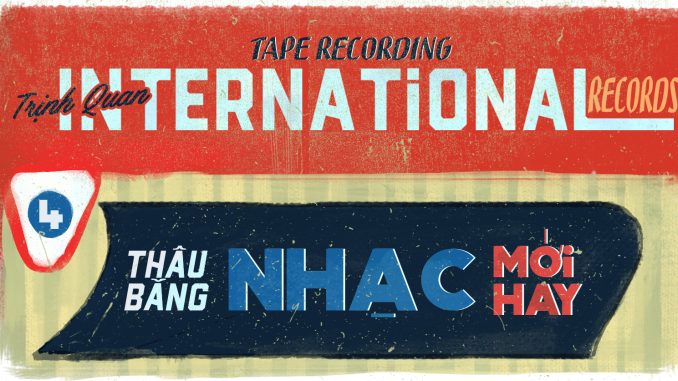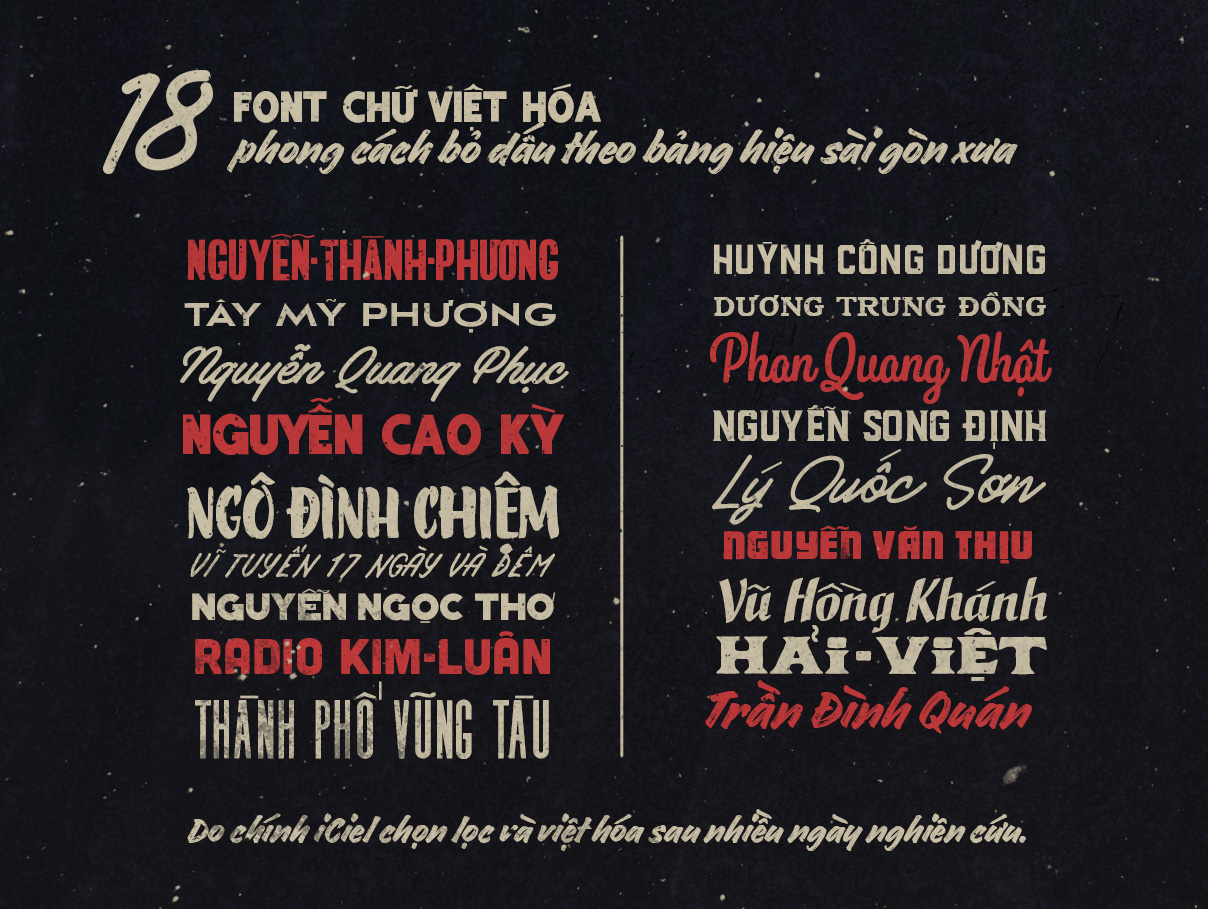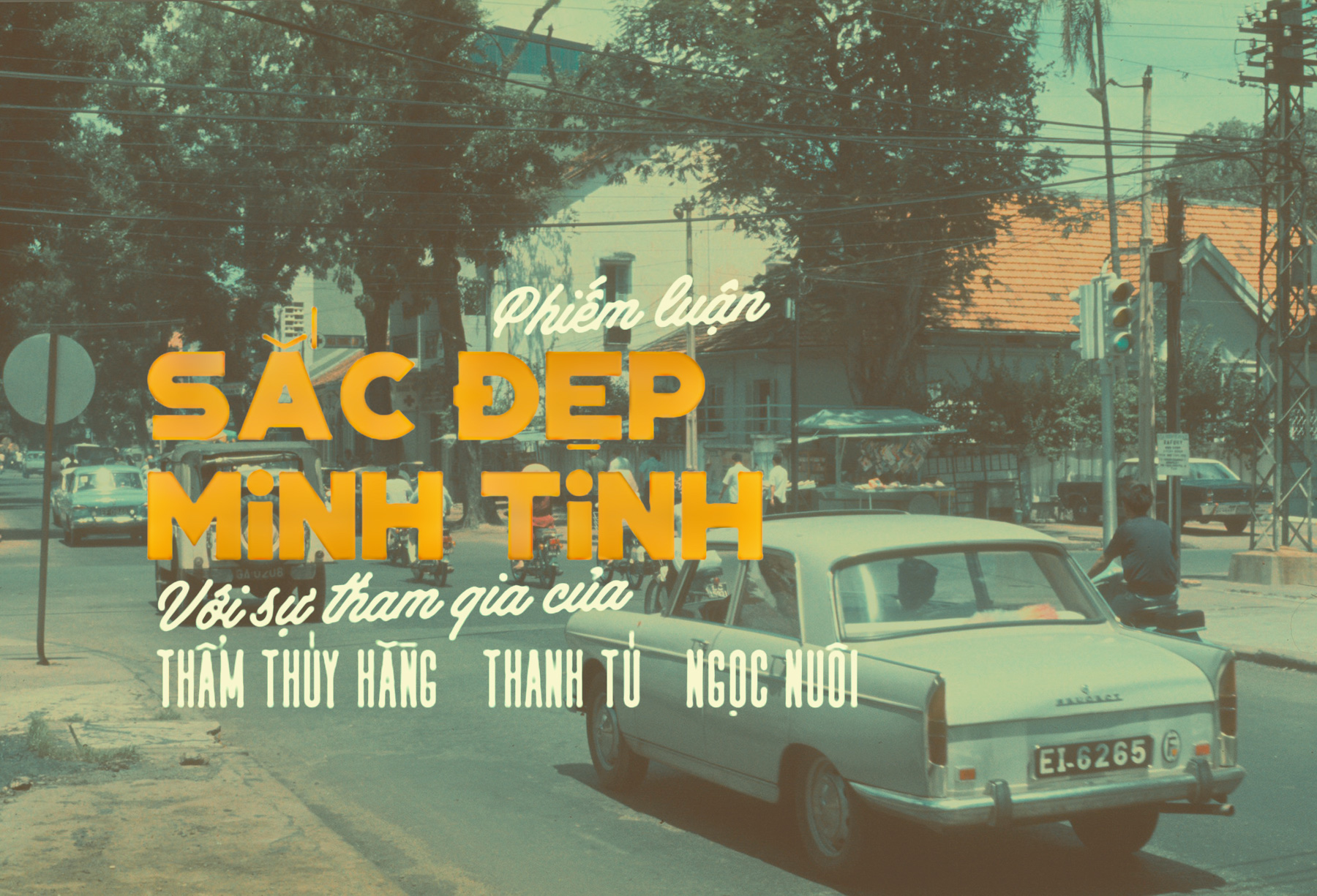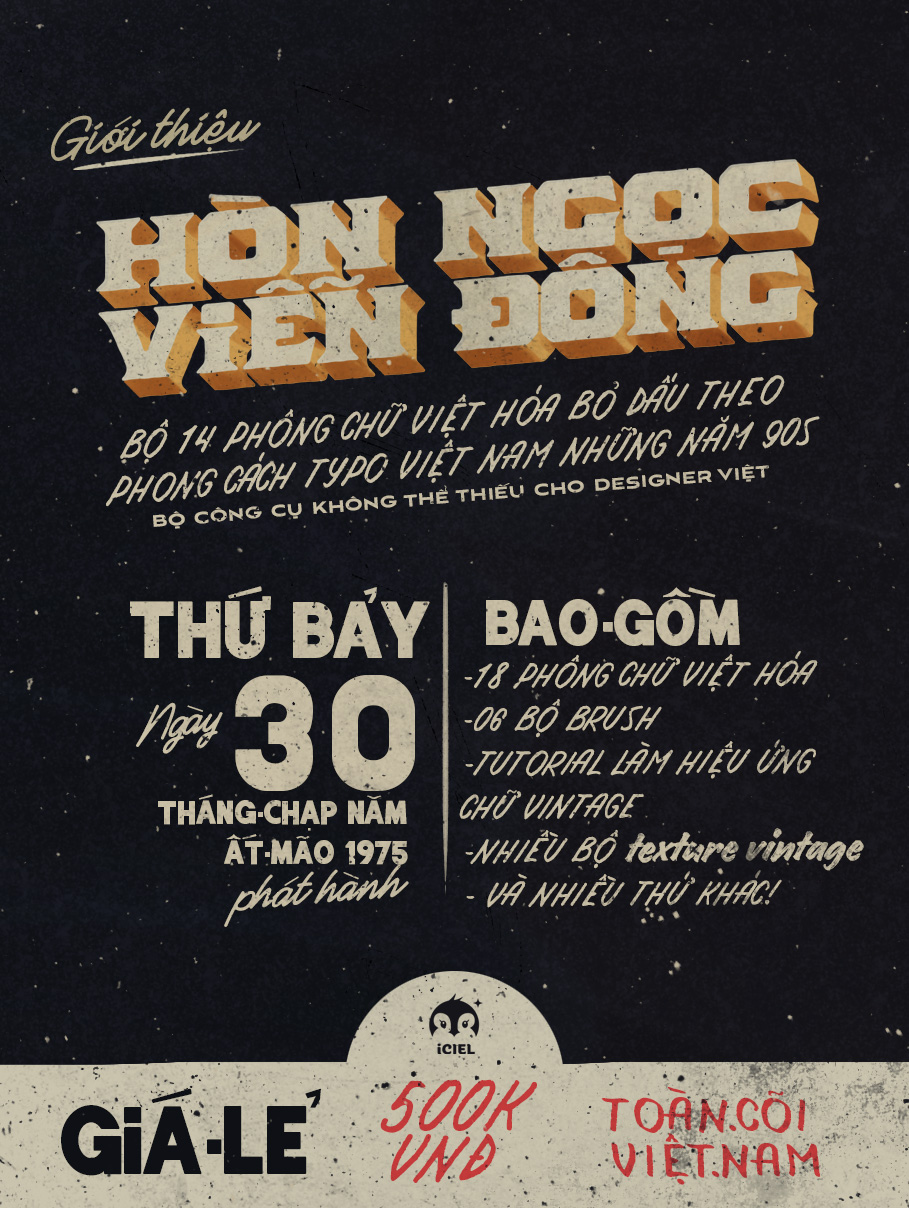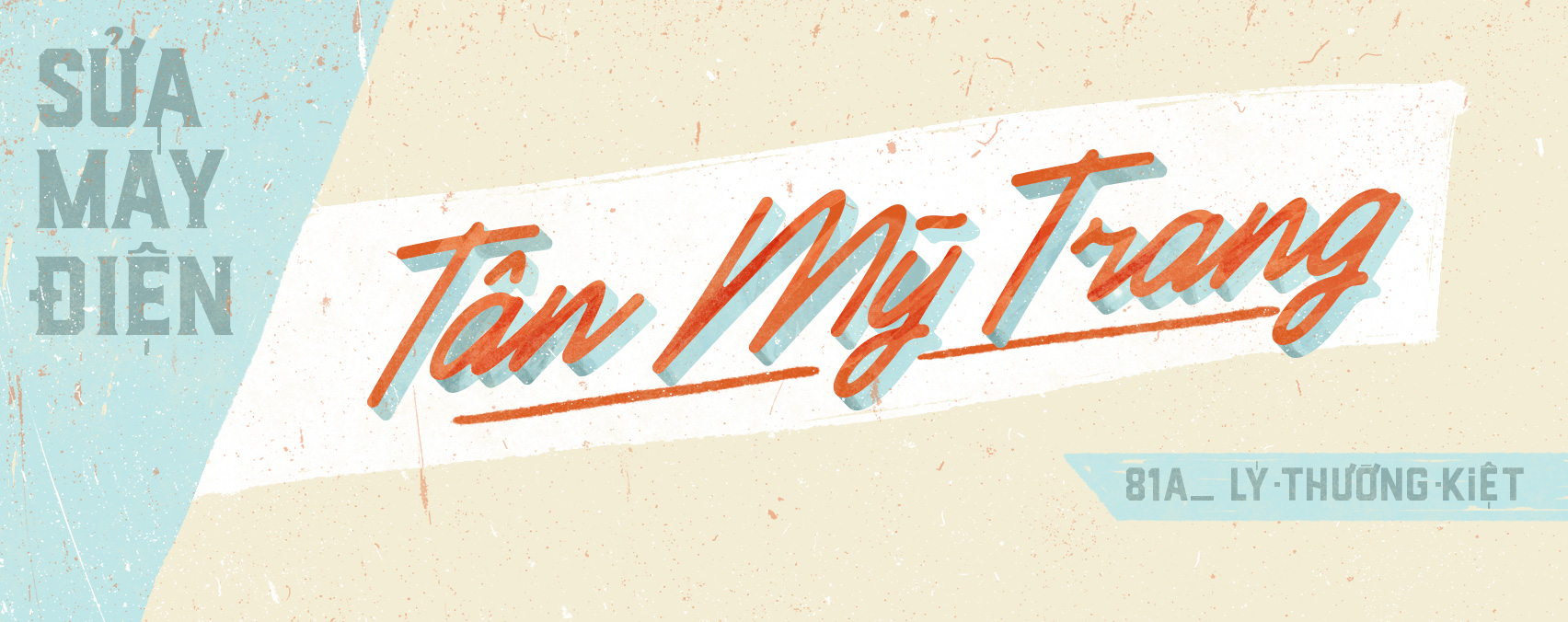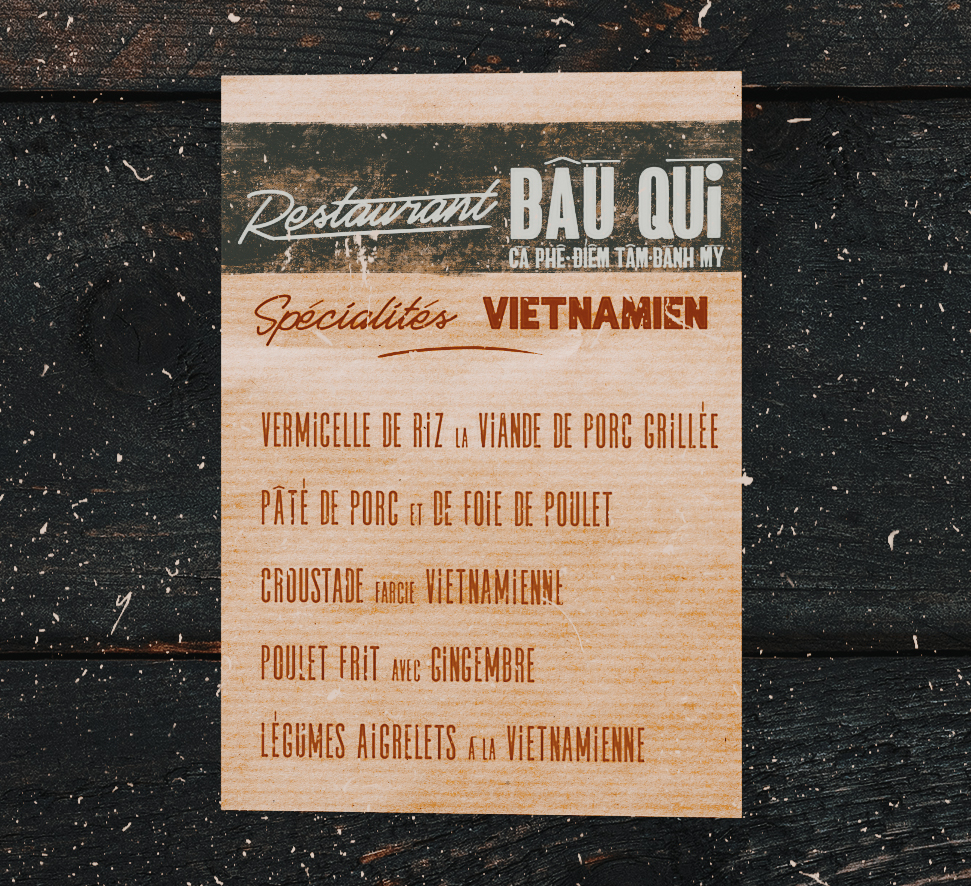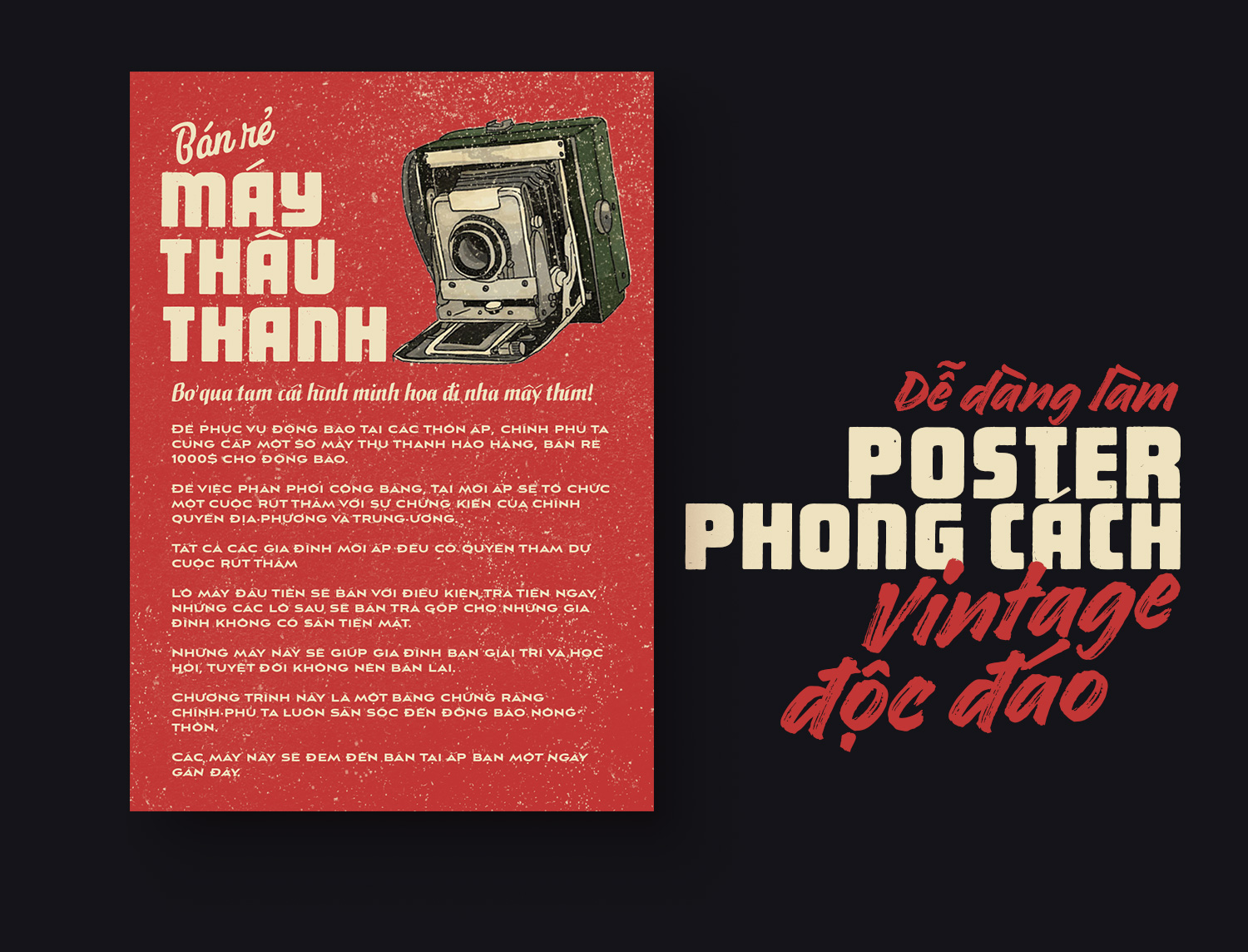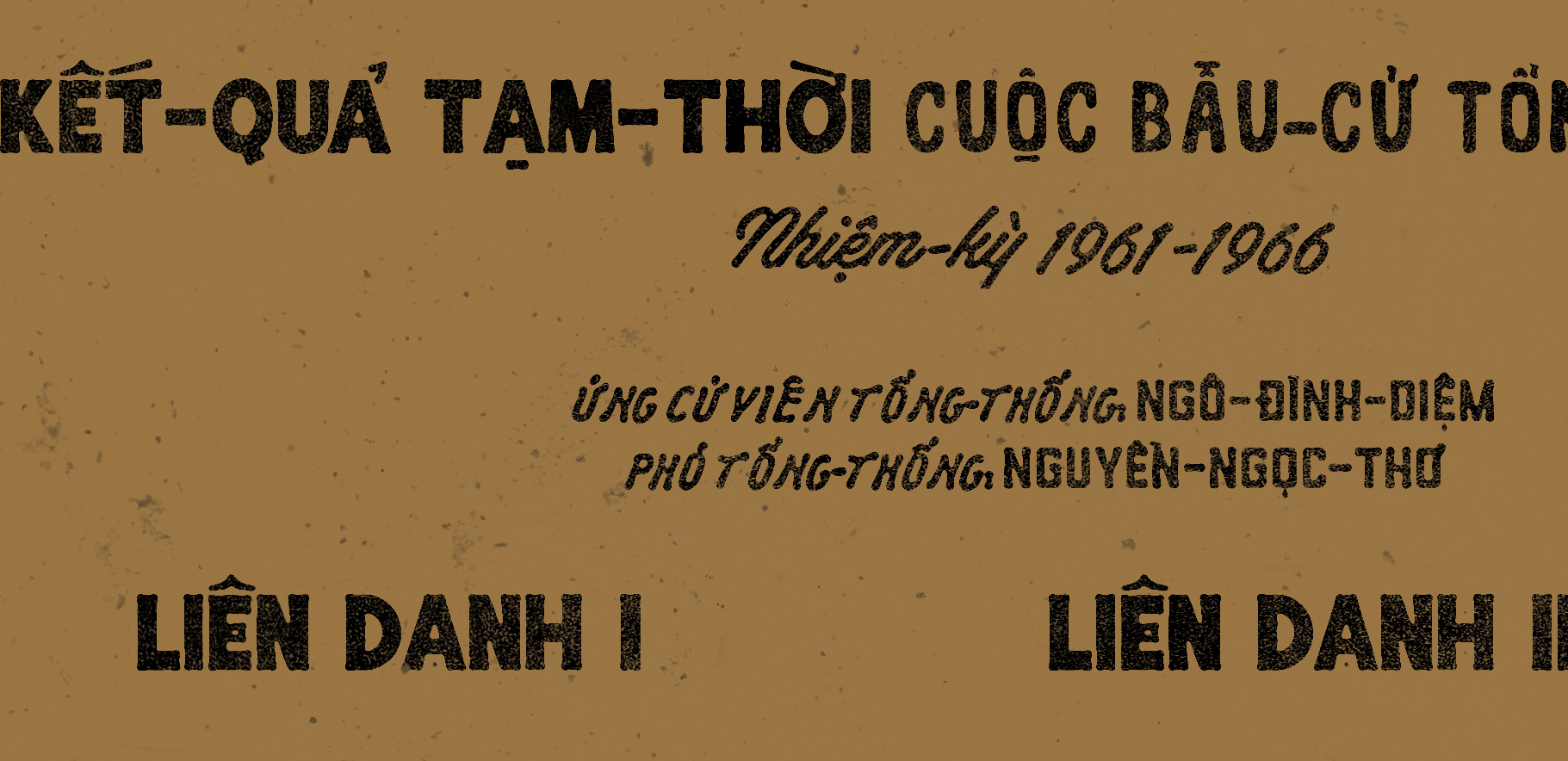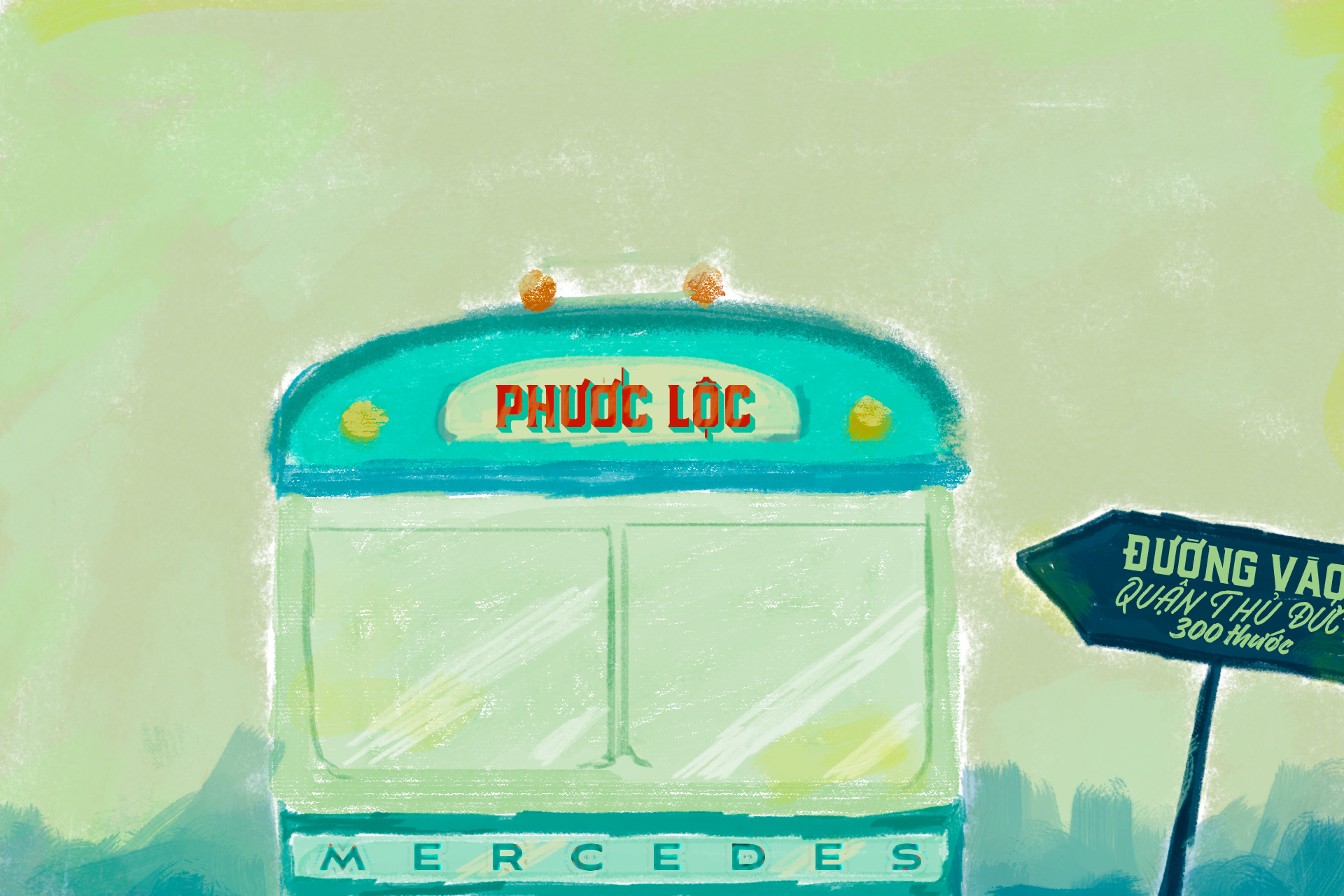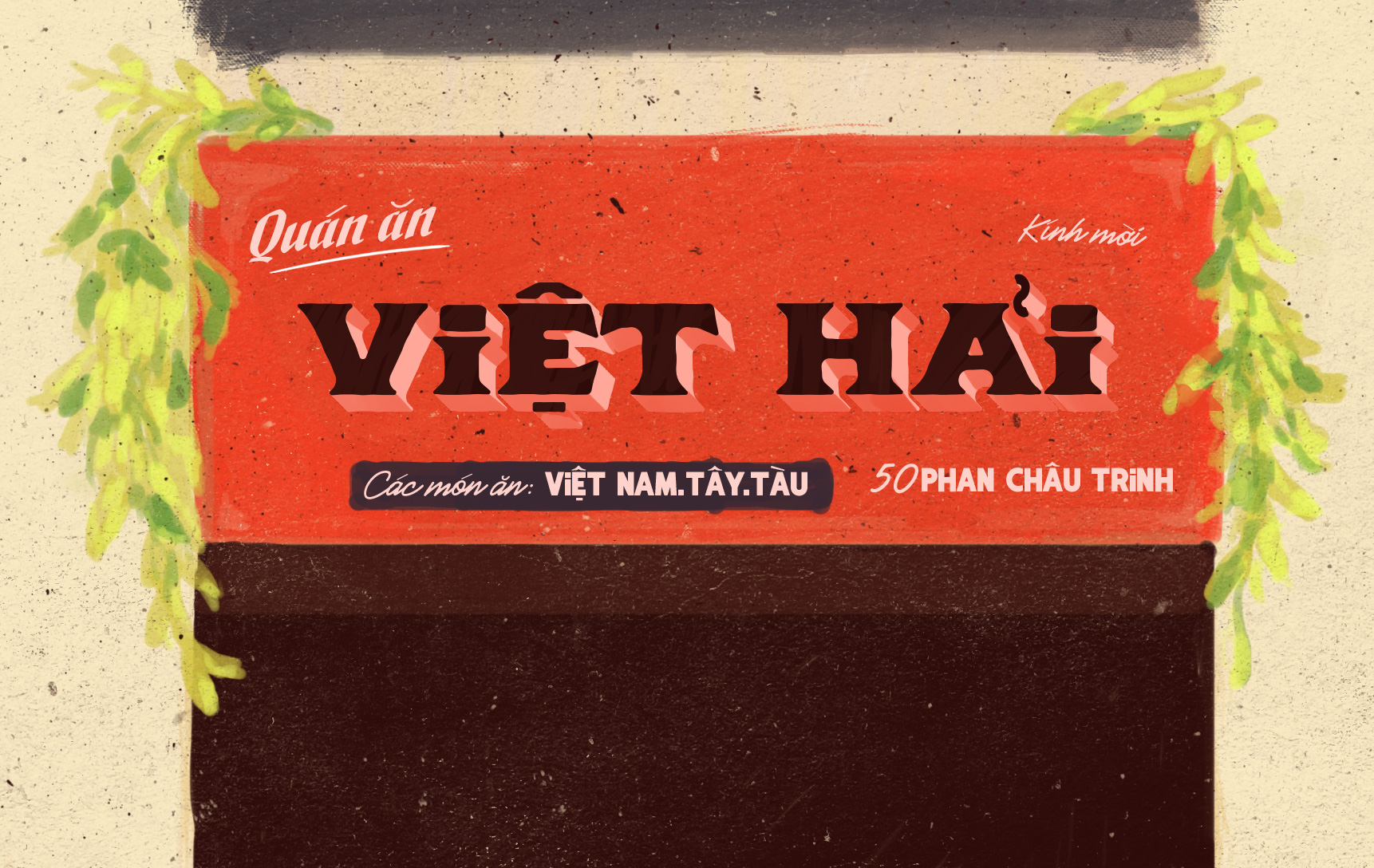
Trọn bộ FULL Font Hòn Ngọc Viễn Đông
Sản phẩm tiếp nối thành công từ bộ font Giá trị Xưa cũ cũng của iCiel, tất nhiên cả 2 bộ font này đều có phí. Trong đó, Phông chữ “HonNgocVienDong” mang phong cách xưa cũ, dựa trên ý tưởng gợi nhớ về các bảng hiệu Sài Gòn xưa, logo từ thế kỷ 19, thời điểm mà Sài Gòn còn được ví như Hòn Ngọc Viễn Đông của châu Á.
Đôi nét về bộ Font Hòn Ngọc Viễn Đông của iCiel
Thực ra, trào lưu tái hiện Font chữ thời xưa tại Việt Nam đã xuất hiện trên Facebook thời gian gần đây. Nhưng để biến những ý tưởng đó trở thành sản phẩm thực tế để nhiều người có thể sử dụng thì không phải ai cũng làm được, nhất là với các bạn không chuyên về thiết kế phông chữ.
Bộ Font Hòn Ngọc Viễn Đông Việt hóa do bạn Nguyễn Hồng Nhung, chủ sở hữu thương hiệu iCiel, thiết kế dựa trên phong cách bảng hiệu Việt Nam thập niên 90. Nắm bắt tâm lý của nhiều người dùng Việt ưa dùng cái gì đó đậm nét bản sắc dân tộc và mang hơi hướng trở về thời kỳ xưa cũ, vì thế mà iCiel đã cho ra mắt bộ phông mới mang tên “Hòn Ngọc Viễn Đông”.
Tác giả đã mất 2 tháng tìm tòi nghiên cứu để giới thiệu bộ font Hòn Ngọc Viễn Đông mang đậm phong cách Sài Gòn xưa, với 18 font chữ được Việt hóa theo phong cách Vintage. Đây là bộ Font độc quyền không có nơi nào sở hữu. Tác giả phải nghiên cứu hàng trăm bức ảnh bảng hiệu Sài Gòn, rồi chỉnh sửa, thiết kế sao cho đẹp mắt nhất, nhưng vẫn giữ được cái hồn của kiểu chữ xưa.
Đúng như tên gọi, bộ Font tái hiện một Sài Gòn xưa từng được ví như “Hòn Ngọc Viễn Đông” tráng lệ, nơi mà bộ mặt đô thị phủ đầy các biển hiệu, logo đậm chất nghệ thuật, được làm thủ công với nhiều màu sắc cầu kỳ từ thế kỷ 19.